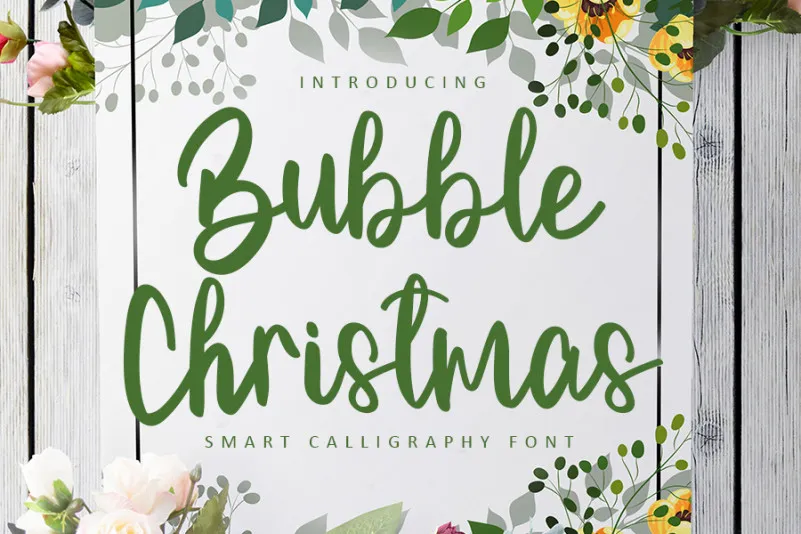
Bubbke Christmas Script Font – Download Grátis
A Bubbke Christmas Script Font é uma elegante tipografia feita para aqueles que buscam uma aparição mágica no Natal. Seus caracteres deslizam suavemente sobre a linha de base, criando um efeito romântico e quente. É perfeitamente adequada para diversos estilos de design que precisam de um toque personalizado, como convites de casamento, cartões de agradecimento, celebrações, cartas de boas-vindas, logotipos e muito mais. Como uma fonte feita à mão pela freshtypeink, ela oferece um desfile atraente que se destacará em qualquer projeto natalino ou especial do fim do ano. Com sua forma delicada e suave, esta fonte é uma ótima adição para quem deseja trazer um ar de sofisticação e romance a seus projetos digitais.